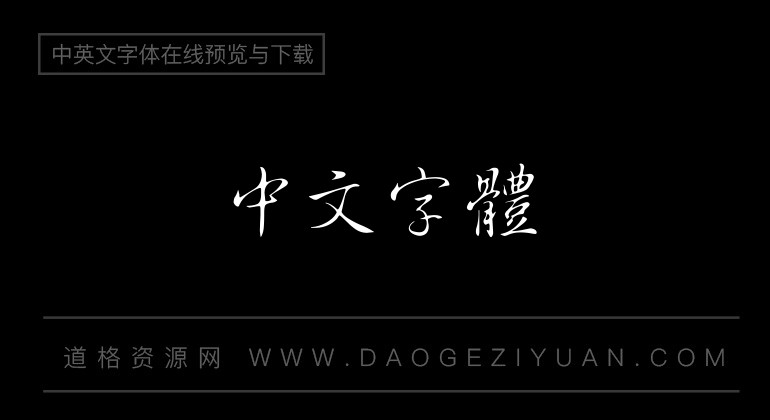
青鸟华光繁行草
青鸟华光繁行草字体是由华文设计师青鸟设计的一款中文行书字体,这款字体以清新、简洁、繁行的特点著称,是一款中国传统文化的经典代表。青鸟华光繁行草字体以中国传统篆刻艺术为基础,结合现代设计技术,深度挖掘篆刻的精髓,结合繁行书的特点,融入清新的设计风格,为用户提供更多的设计资源。青鸟华光繁行草字体具有传统篆刻艺术的精髓,也具有现代繁行书的特点,可以应用于各种类型的文字设计,是一款非常优秀的中文字体。
青鸟华光繁行草是一款非常不错的手写艺术字体,具有很好的视觉感,适合于文化类的宣传设计、商业类品牌的广告和产品包装设计以及个性化文字排版等较多场景。